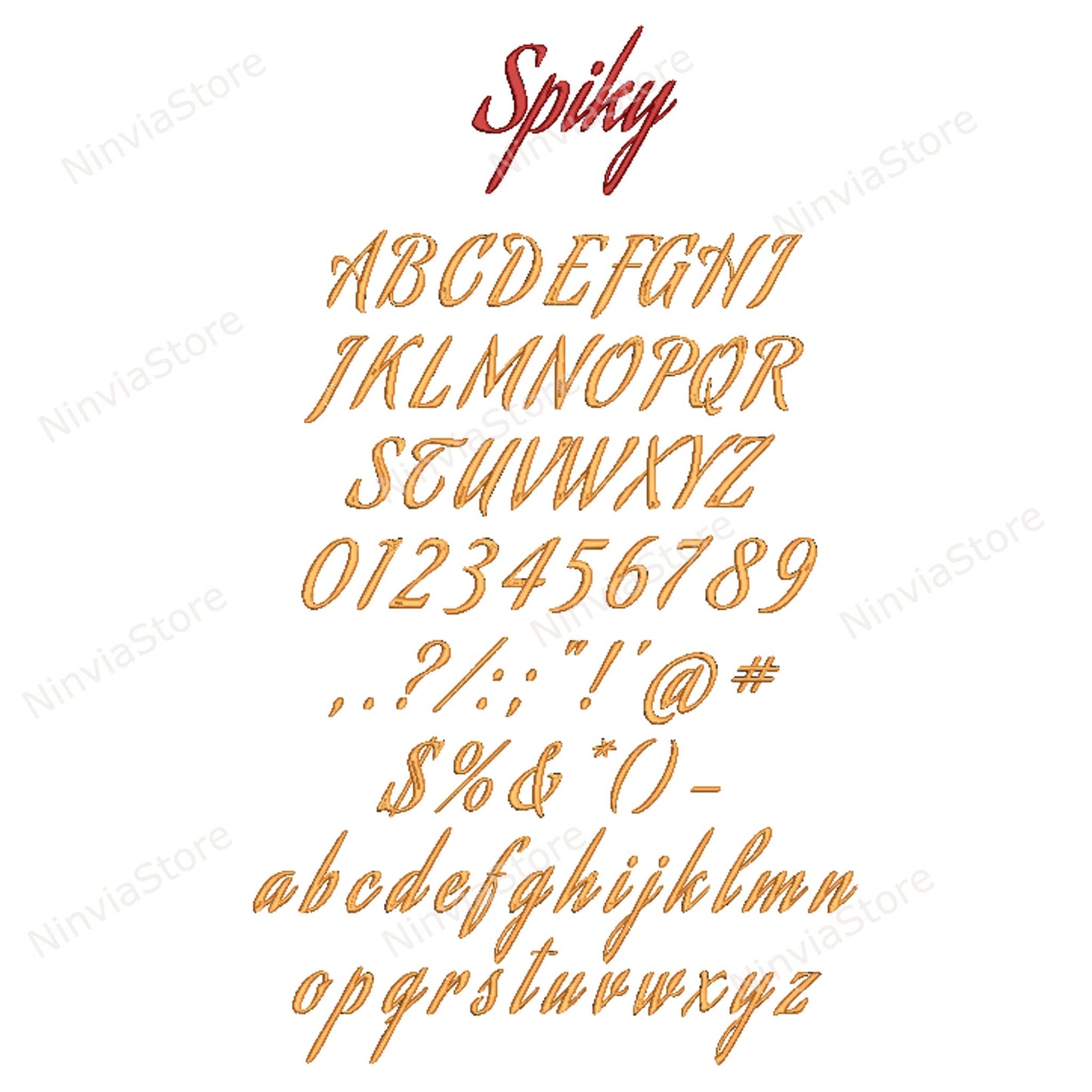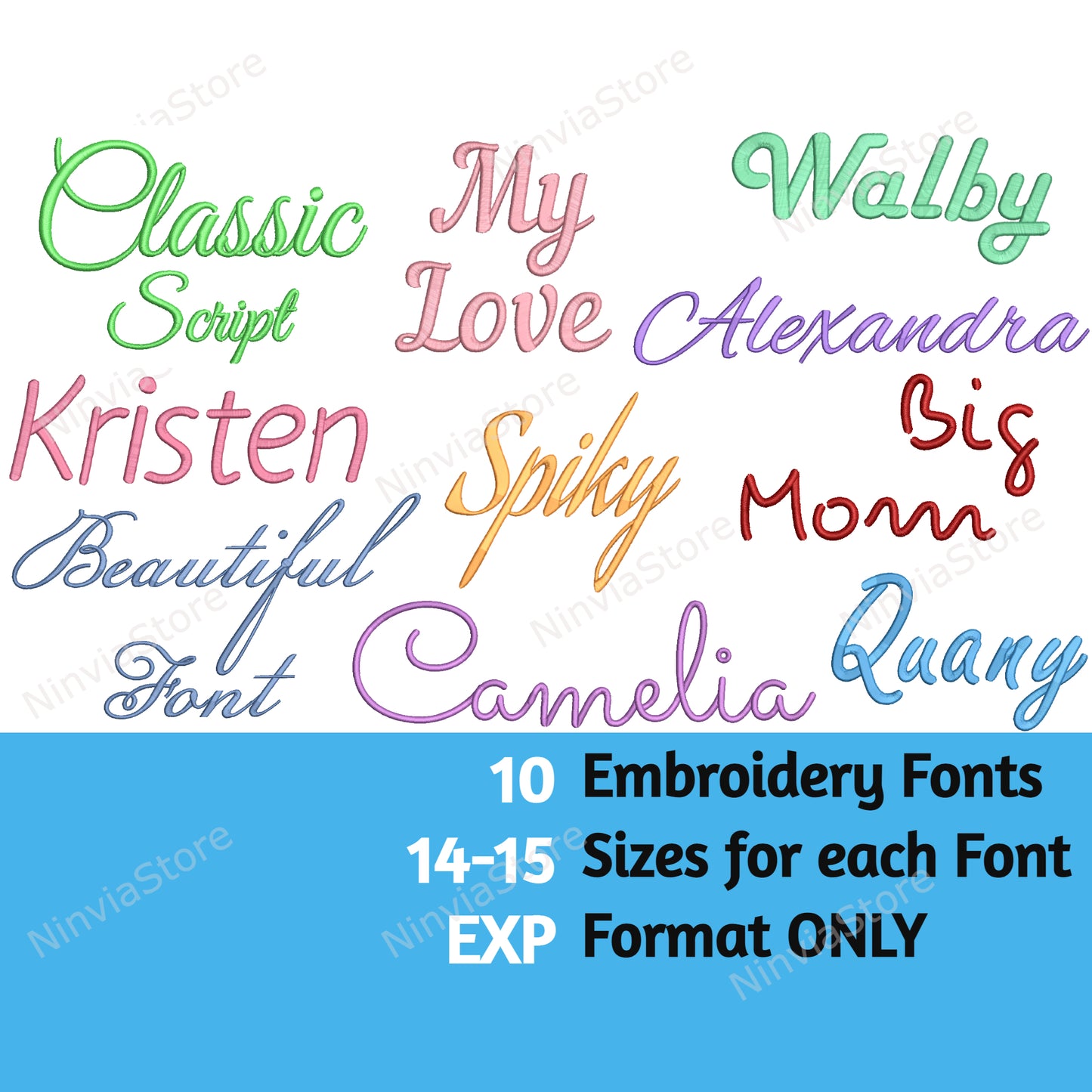
10 EXP broderie Script polices Bundle, Alphabet broderie Design, machine broderie police EXP, cursive EXP police pour la broderie, calligraphie monogramme broderie police EXP
***CAMÉLIA***
***CLASSIQUE***
***BEAU***
***MARCHE***
***PIQUÉ***
***ALEXANDRE***
***MON AMOUR***
***GRANDE MAMAN***
***KRISTEN***
***QUANY***